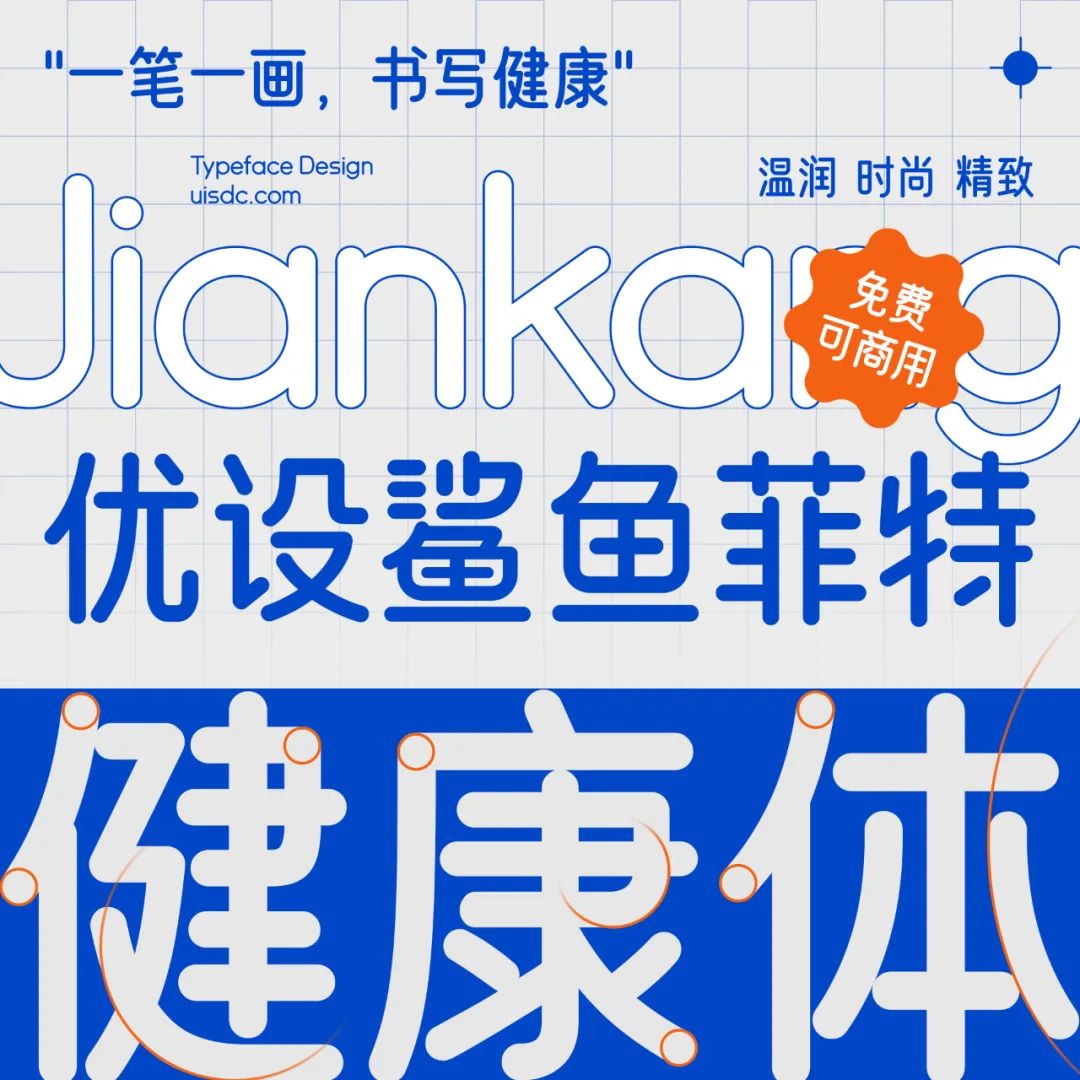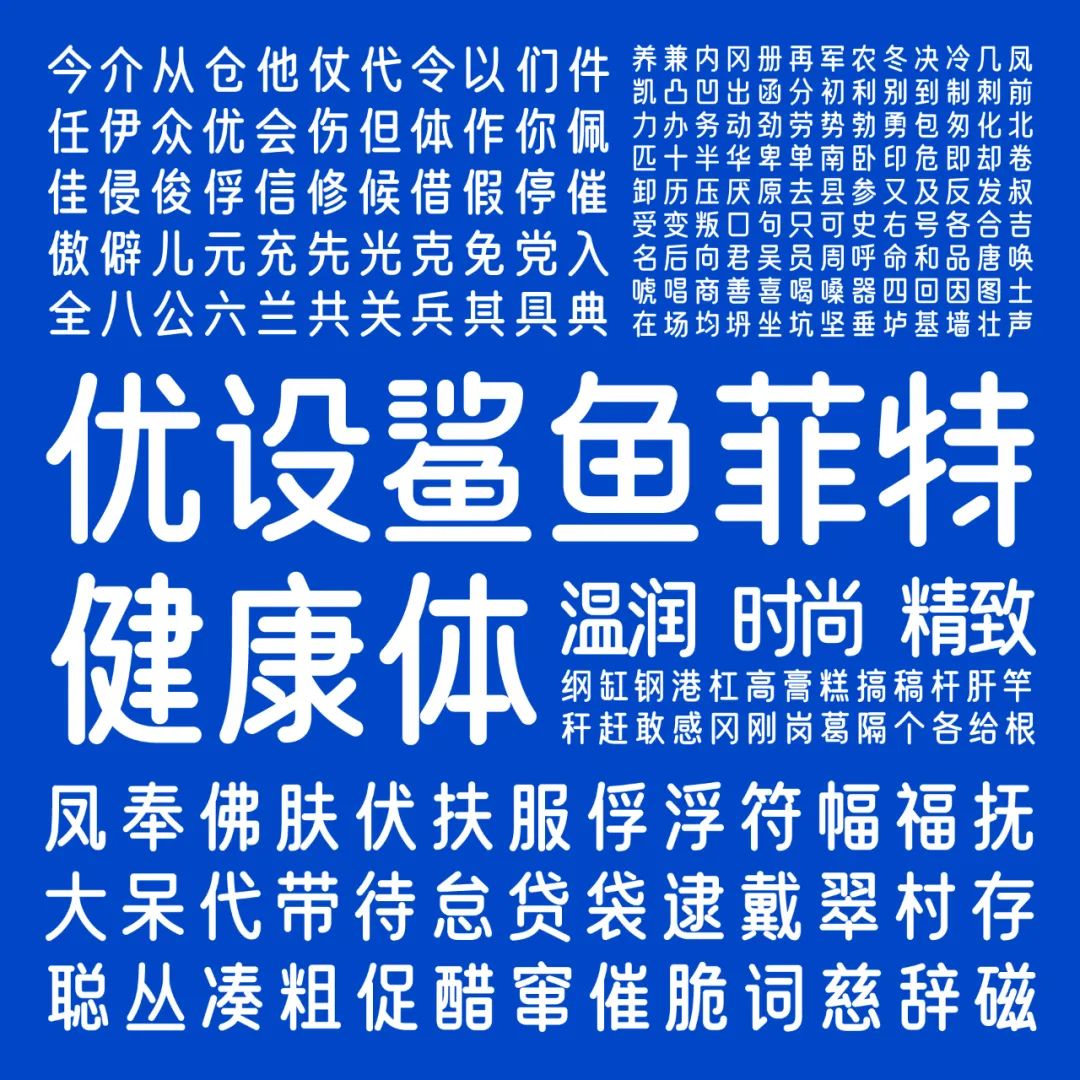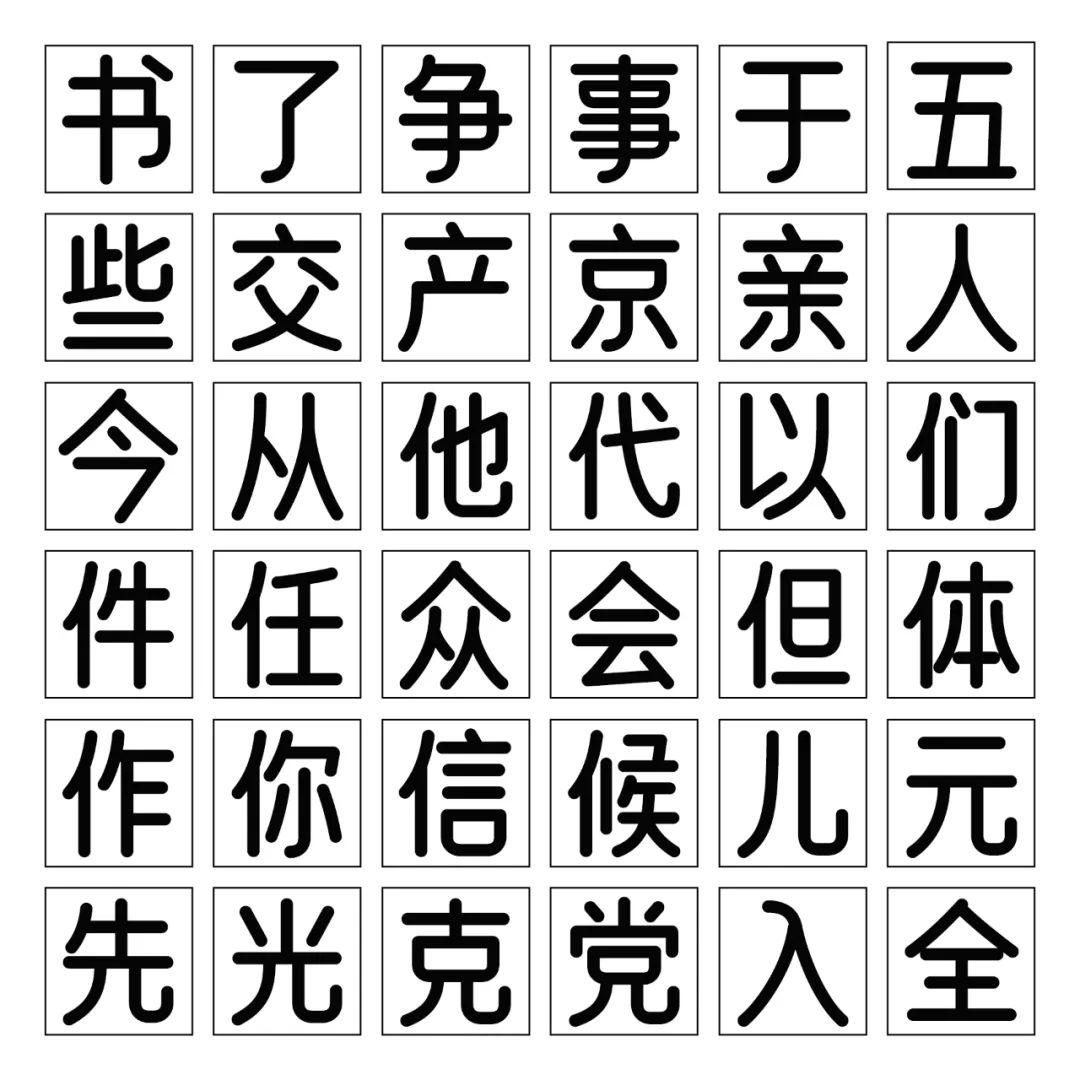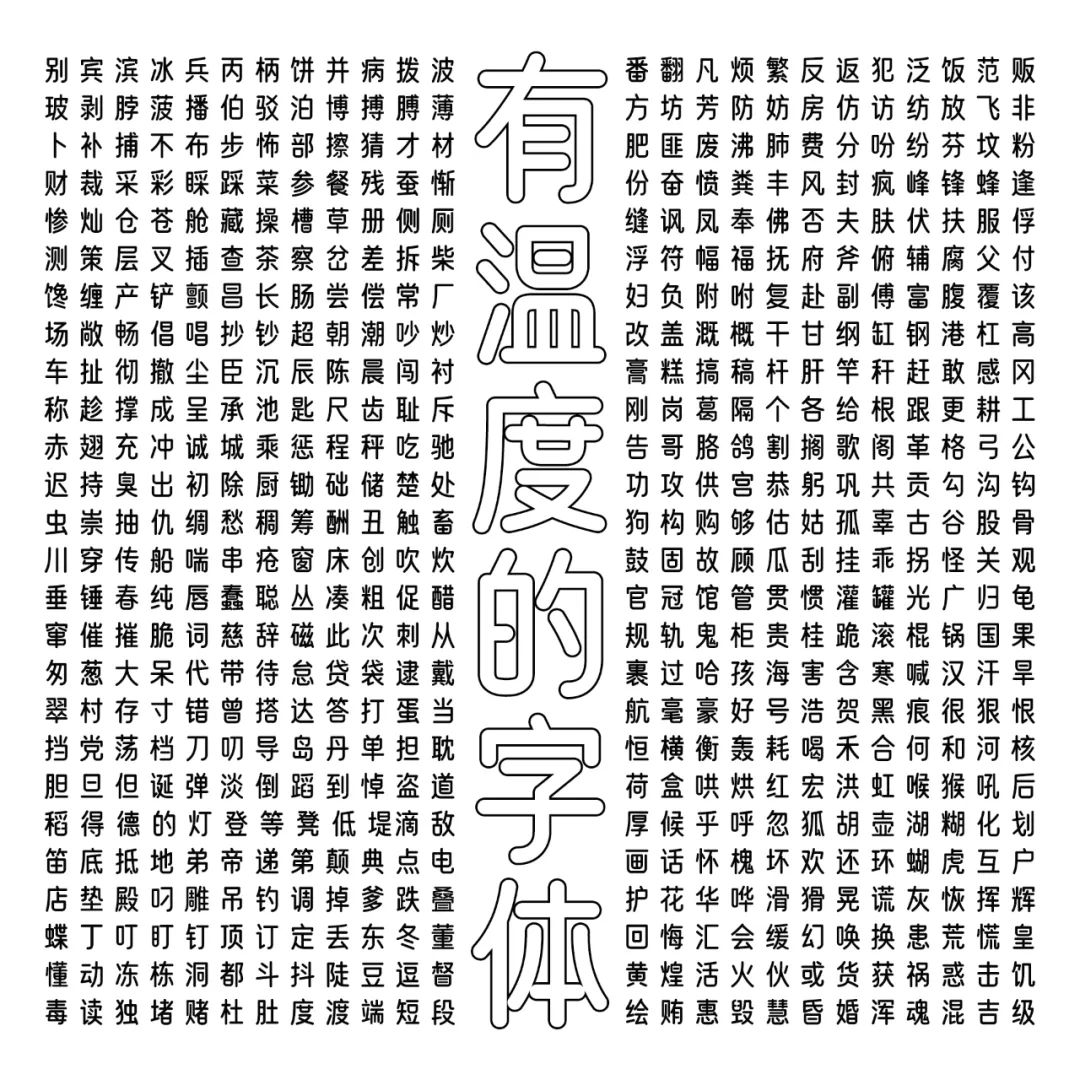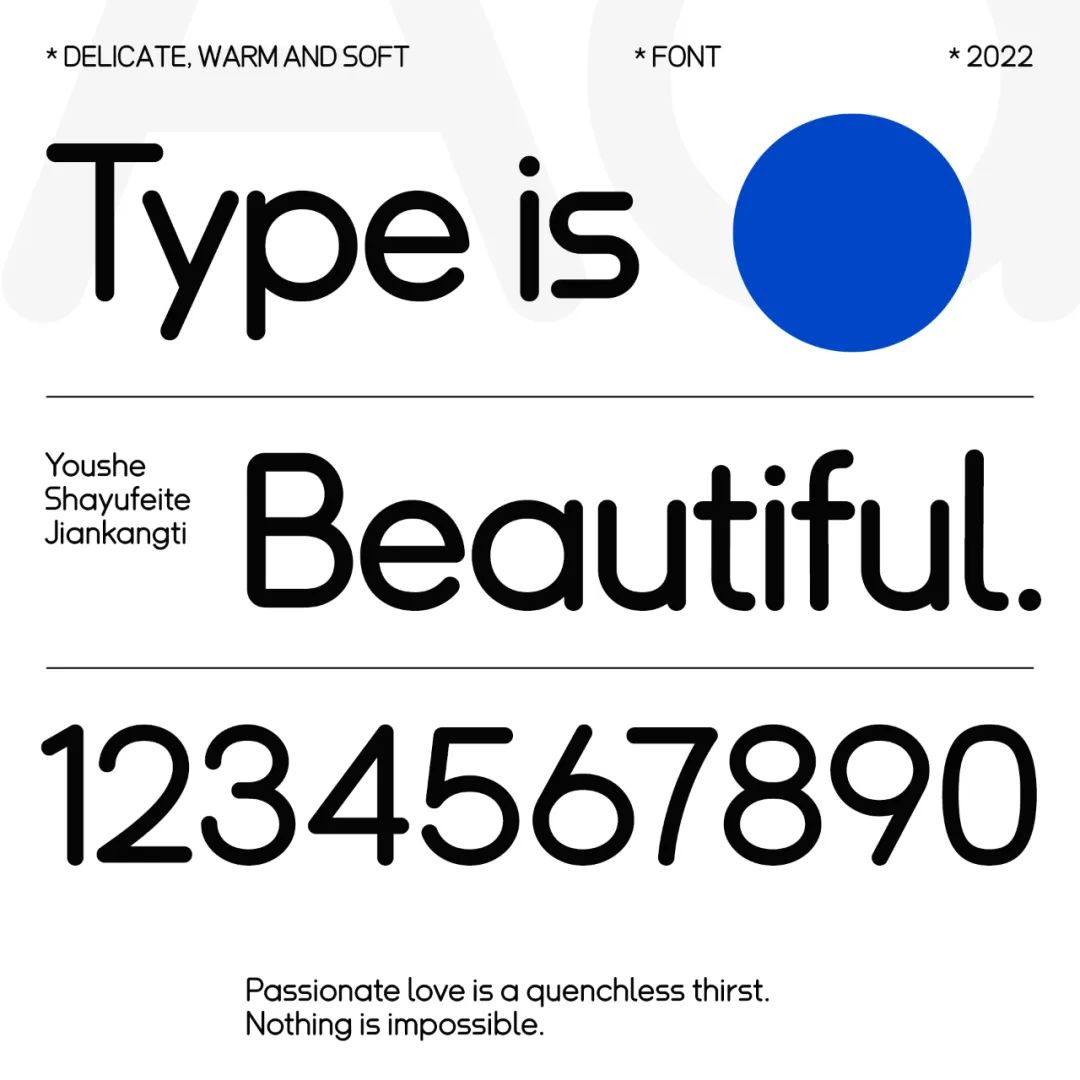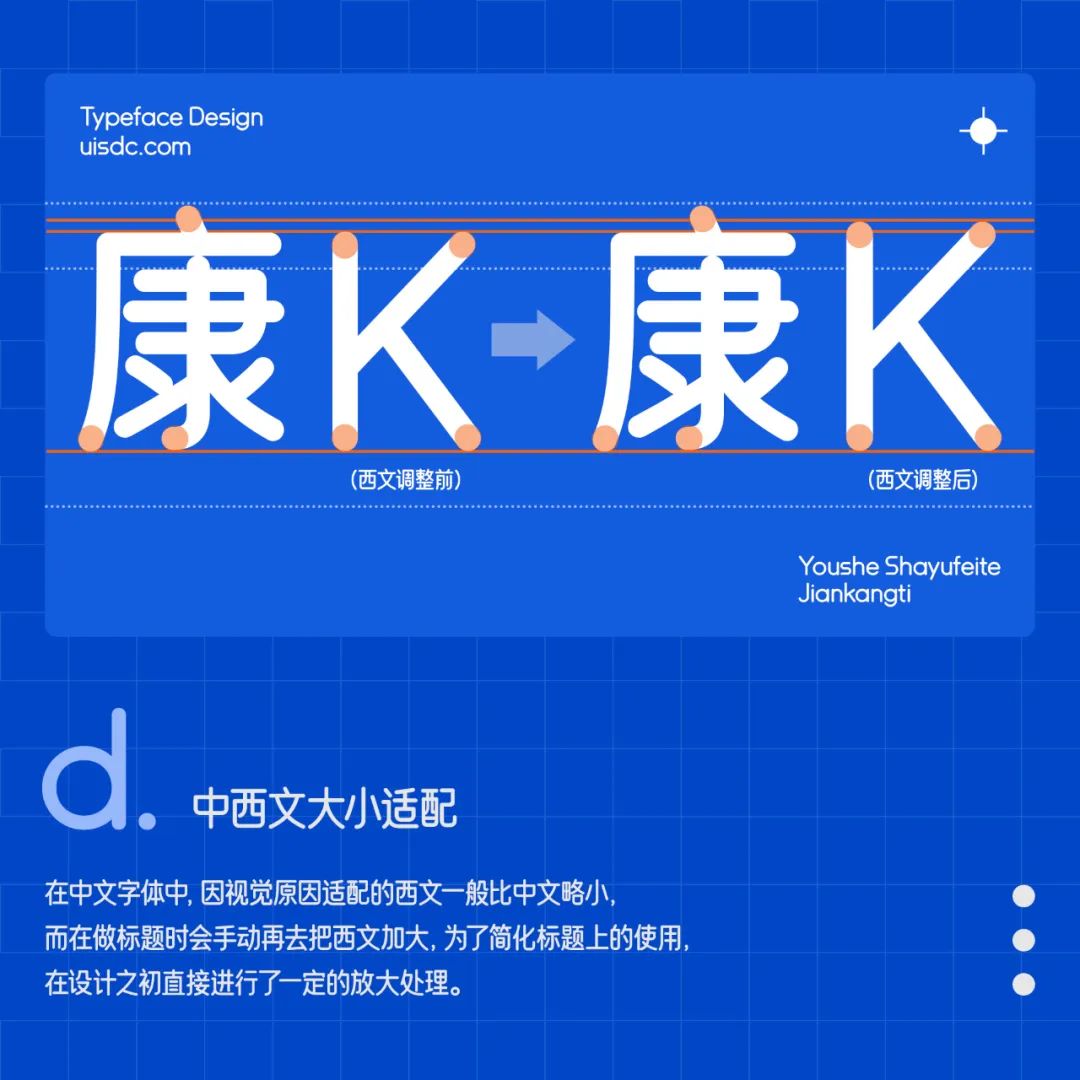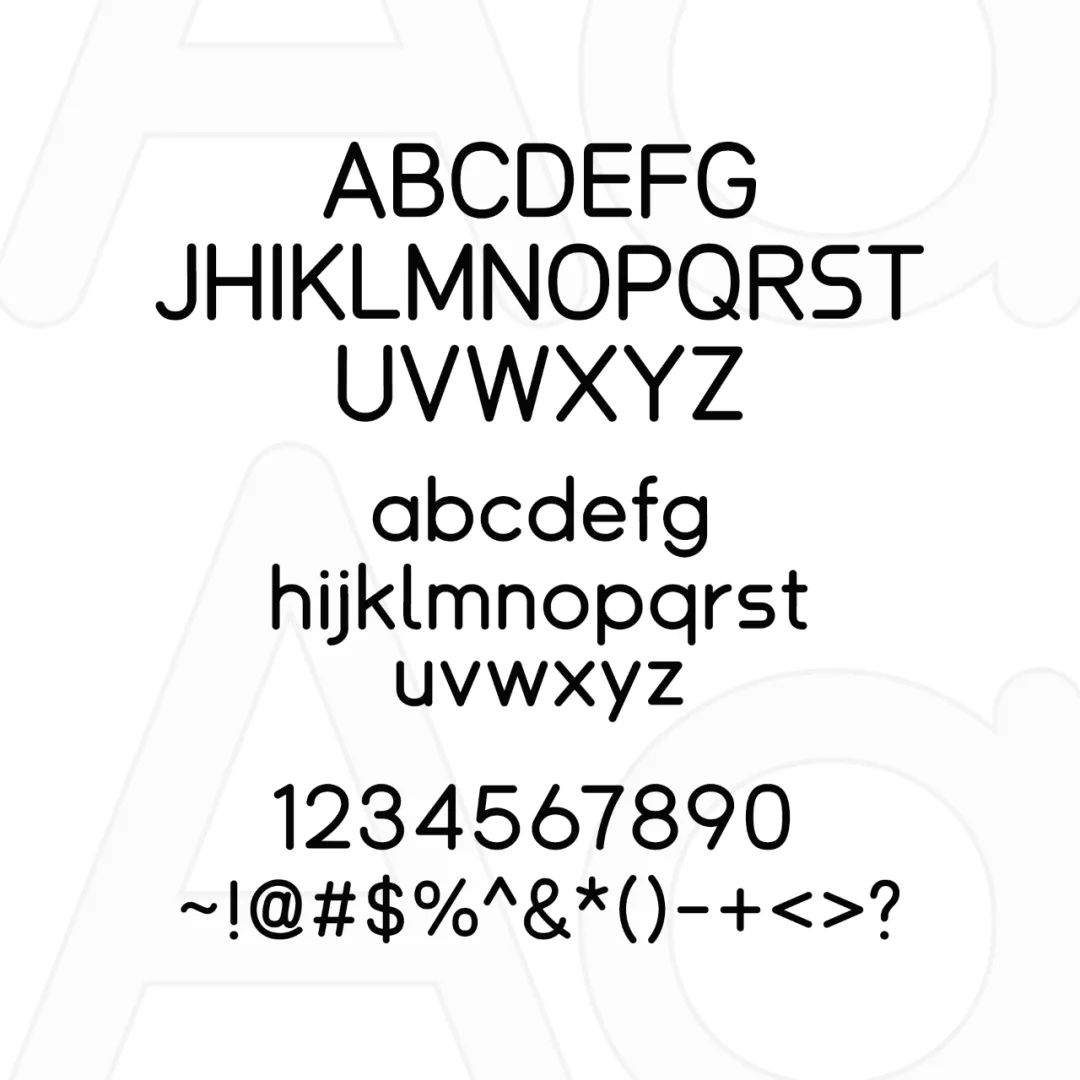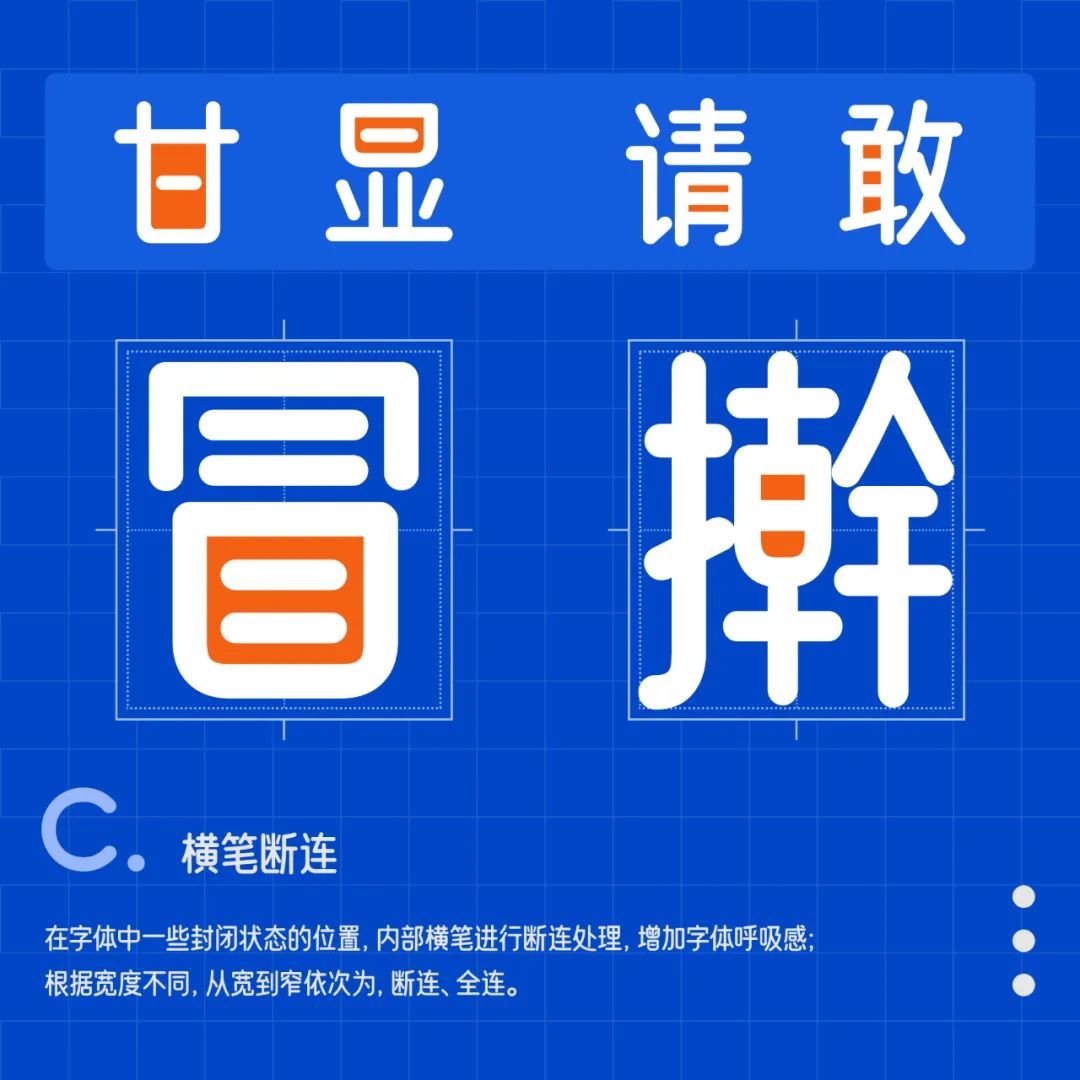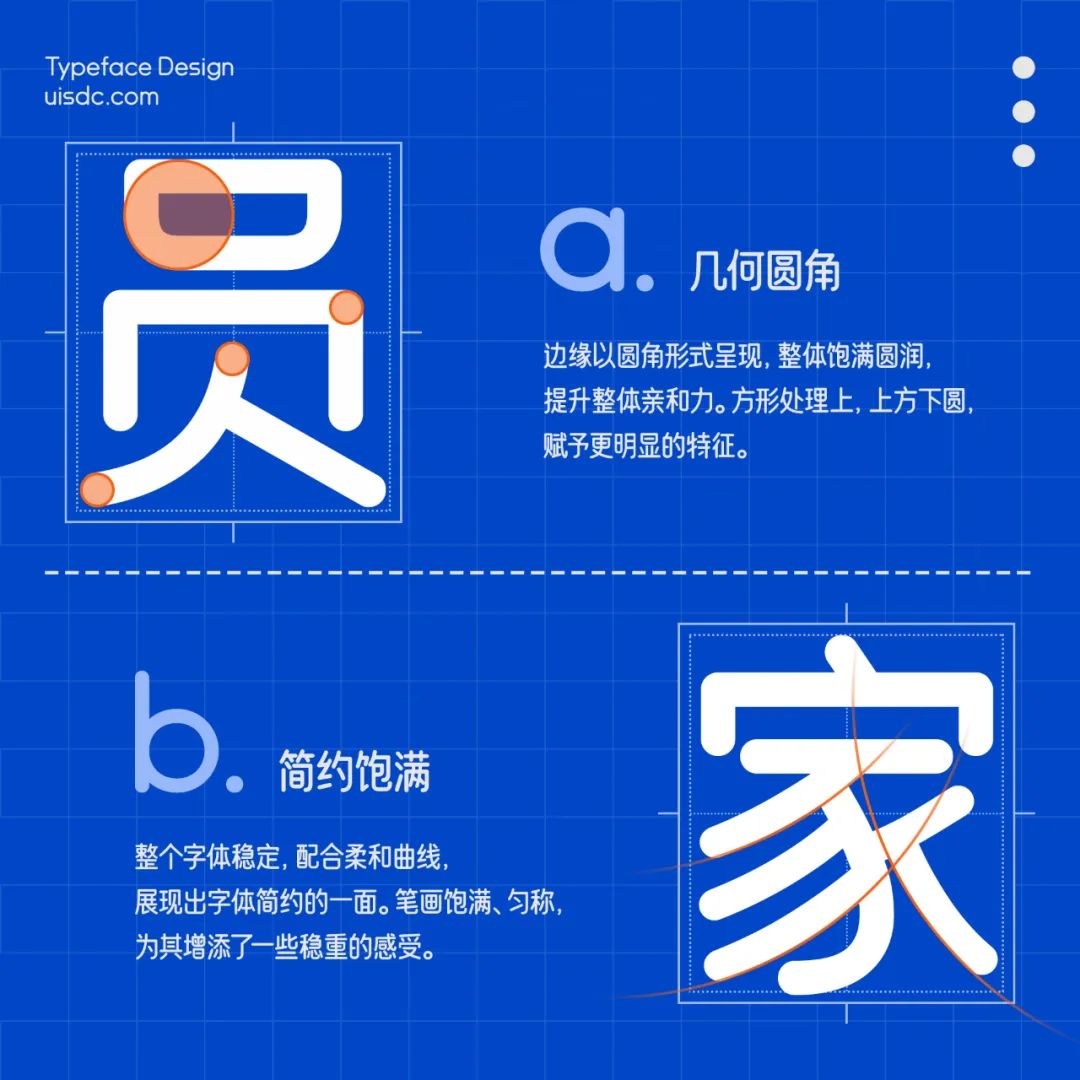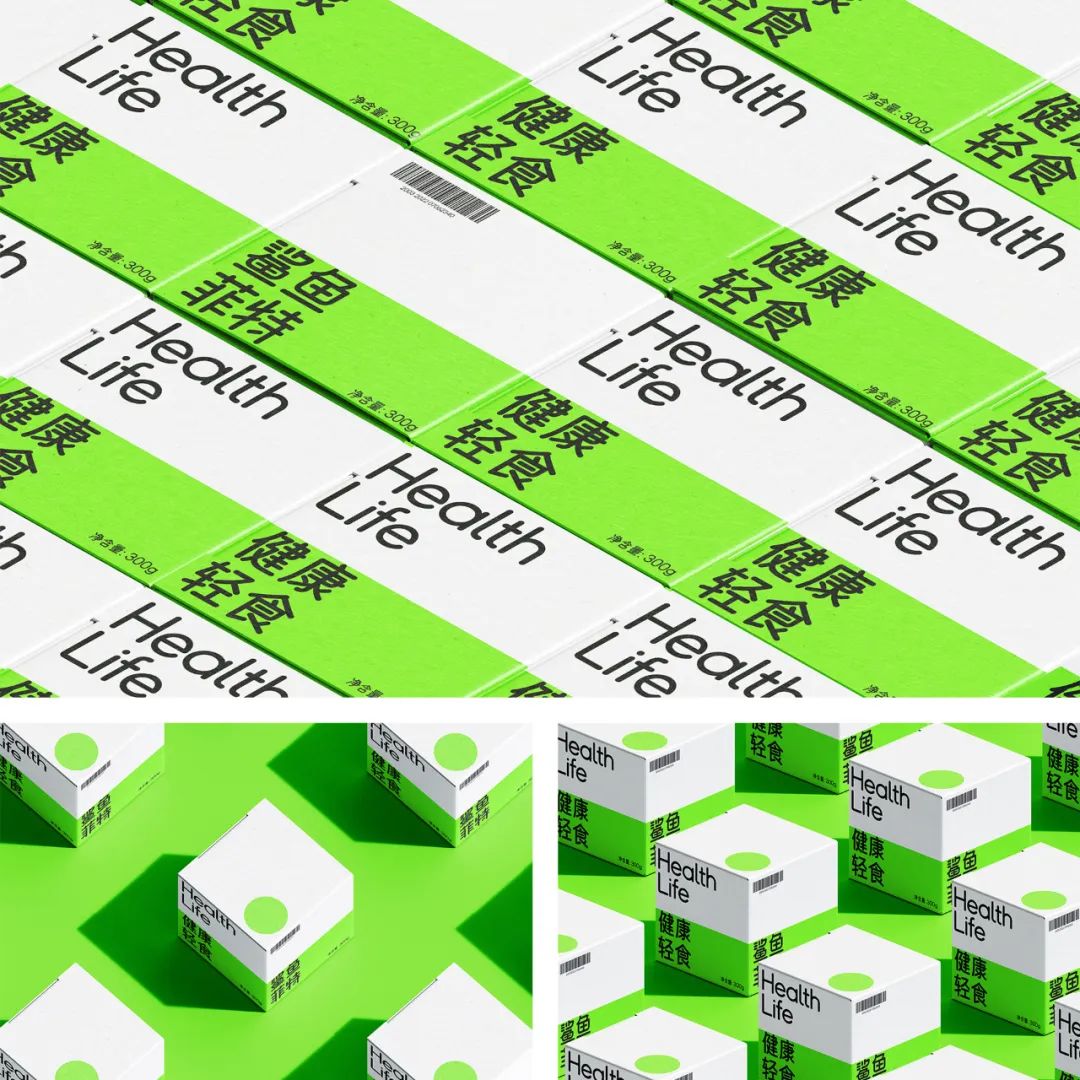
一款专为健康而生的免费字体,请放心食用~
由字绘中国发起,新零售健康轻食品牌鲨鱼菲特联合优设与字由,为广大设计师特推出了一款专为健康而生,电商应用场景极强的优质字体——优设鲨鱼菲特健康体。
这已经是优设的第5款免费字体了,前4款都已上线字由,并成为了设计师们必不可少的宠儿。
这款鲨鱼菲特健康体,由优设及字由共同设计,是优设好身体的升级版,造型上要比优设好身体更具有辨识度,设计上更加贴近健康品牌附有的亲和力和现代感,不仅会成为电商设计的又一大助力,更体现了当下Z时代年轻用户追求健康的群体特性。
字体设计之初是作为健康轻食品牌“鲨鱼菲特”的品牌 logo 去创作设计的,所以既要展现健康年轻态,也要有满满的亲和力。
整套字体在圆润的外观和优美的弧度下,对字形、笔画细节进行了再设计,结构纵向拉长,体现健康体态的纤细匀称感;同时在一些细节之处,加了一些硬挺的视觉感,使字体看起来轻快时尚,又不失精致与稳重感。
一起来看看实际应用的效果吧~